Tổng Hợp Những Font Chữ Thiết Kế Thiệp Cưới Ấn Tượng Nhất 2021
Để chiếc thiệp cưới của bản thân trở thành dấu ấn hơn với khách mời. Không chỉ nằm ở việc đem những ý ý tưởng hấp dẫn vào trong thiết kế thì việc quyết định phông chữ. Là một điều trọng yếu khiến chiếc thiệp của bạn trở thành nổi bật hơn. Sang trọng hơn hoặc mang phong cách của riêng cặp đôi ấy .
Phông chữ thiệp cưới là gì ?
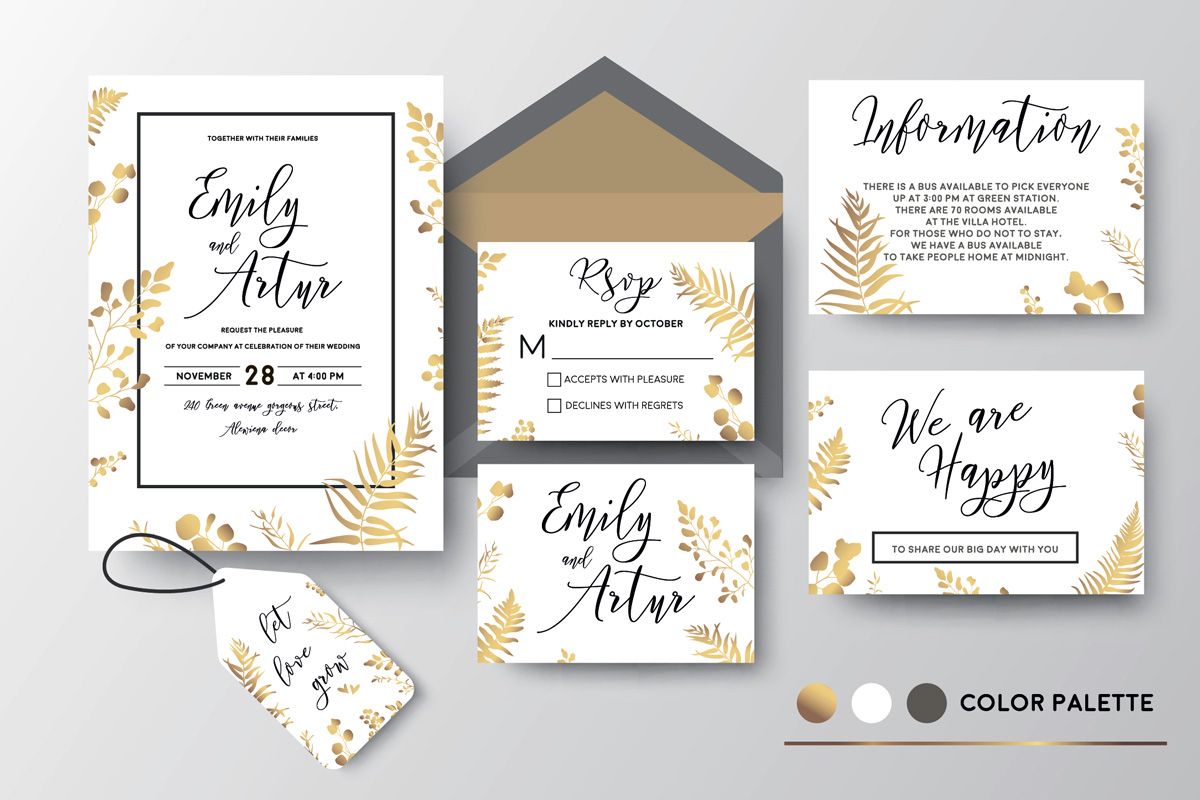
Phông chữ thiệp cưới là bộ font sử dụng để in lên giấy mời tiệc cưới của nhiều đôi tình nhân. Chính bởi tiệc cưới thường là kết quả của một tình yêu mơ mộng. Tính gắn kế nên lúc in thiệp cưới nhiều người thường dùng những phông chữ gần y như :
- Font thư pháp
- Font nghệ thuật ….
Phông chữ thiệp cưới hiện tại rất phong phú, đa dạng, ngoài các font thuần việt. Thì cũng có hàng chục font được việt hóa để sử dụng cho các việc có liên quan đến xây dựng trong tiệc cưới. Các bộ font này phân phối nhiều phông chữ theo các phong cách hình ảnh không giống nhau. Độ phù hợp hầu như hoàn chính với bộ gõ tiếng việt như Unikey hoặc Vietkey. Làm cho bạn thi hành thao tác đơn giản hơn, các lệnh biên tập thông tin trở thành đơn giản.
Hơn thế nữa các phông chữ thiệp cưới có khả năng được sử dụng để đề dòng chữ lên giấy mời cưới. Hoặc làm nên các text trong những hình ảnh cưới tráng lệ với các nét chữ đẹp và bay bổng.
Nhiều phông chữ thiệp cưới đẹp , được đông đảo mọi người thích thích
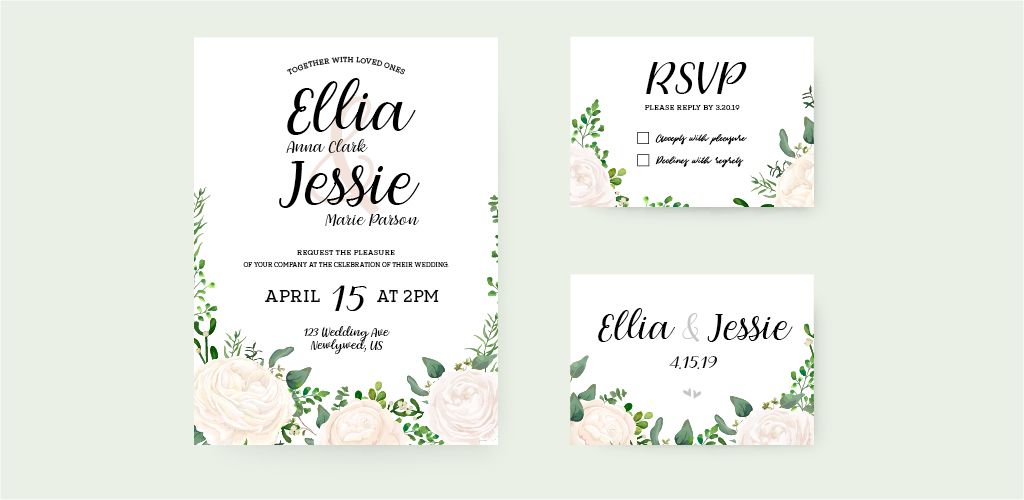
Phông chữ Parfumerie Script Pro
Đây chính là phông chữ xếp đầu trong danh mục những phông chữ thiệp cưới đẹp , ấn tượng nhất . Điểm nổi trội của chúng là có tới 2500 kí tự, trong font có chứa tới 5-7 bản của một chữ a. Được biết phông chữ parfumerie script pro
Được phỏng theo từ chính những chữ viết tay của người viết. Người phát minh ra phông chữ này bởi thế mà nó thật sự mang linh hồn. Của những con chữ như được bạn viết thủ công của bản thân vậy, cực kỳ ấn tượng, rất độc đáo .
Phông chữ Baskerville Display PT
Phông chữ baskerville display pt sẽ giúp bạn có một sản phẩm thiệp cưới nền nã. Tuy nhiên không thua kém phần cao cấp, rất hợp với những tấm thiệp cưới mang phong cách lãng mạn
Font thiệp cưới Splandor
Đây là font chữ mang đậm phong cách cổ điển, nhẹ nhàng tối giản. Với font chữ này chỉ cần bạn thiết kế sáng tạo một chút là bạn sẽ có ngay những tấm thiệp cưới ấn tượng. Font chữ sẽ hợp với những ai yêu thích những nét cổ điển, nhẹ nhàng
Font chữ Copperlove by Resistenza
Đặc điểm của font chữ này là có nhiều kí tự thay thế và đuôi chữ. Copperlove cho bạn thỏa sức sáng tạo những nét chữ đẹp đẽ, uốn lượn theo ý thích. Font chữ này thích hợp với các cặp đôi yêu thích sự hiện đại, trẻ trung.
Font chữ Noelan Script
Là một kiểu chữ thư pháp được cách điệu khá hiện đại từ nhà thiết kế người Indonesia Ndro Adv. Với thiết kế sạch sẽ và hiện đại, Noelan bao gồm các ký tự chữ hoa, chữ thường, số, dấu chấm câu. Noelan có thể kết hợp hoàn hảo với các font chữ cứng để cho ra Typography (.nghệ thuật sắp chữ) có tính thẩm mỹ cao. Thích hợp khi sử dụng thiết kế thiệp cưới lãng mạn, sang trọng.
Những lưu ý khi chọn font chữ thiết kế thiệp cưới
Hiện nay trên thị trường xuất hiện nhiều mẫu thiệp cưới đẹp với những phong cách khác nhau. Đáp ứng nhu cầu đa phong cách mà các cặp đôi hướng đến. Chính vì thế mỗi kiểu thiệp cưới khác nhau sẽ có những mẫu font chữ khác nhau. Cặp đôi nên bàn bạc với phía cung cấp để mẫu thiệp được thiết kế một cách hài hòa nhất.
Bạn cũng không nên sử dụng quá nhiều font chữ trong một thiết kế thiệp cưới. Thường thì 2 font là hợp lý. Bởi việc sử dụng quá nhiều font chữ sẽ khiến cho người đọc bị rồi mắt. Và làm cho tấm thiệp trở nên kém sang trong mắt khách mời.
Ví dụ các bạn có thể chọn phong cách font chữ phù hợp với mình theo gợi ý sau đây. Các cặp đôi thích hiện đại có thể chọn các loại thiệp cưới với họa tiết hiện đại được vẽ tay. Hoặc vẽ màu nước. Đối với các cặp đôi thích phá cách có thể chọn loại thiệp cưới in ảnh cô dâu chú rể, thiệp cưới khắc chữ, thiệp cưới cắt laser…